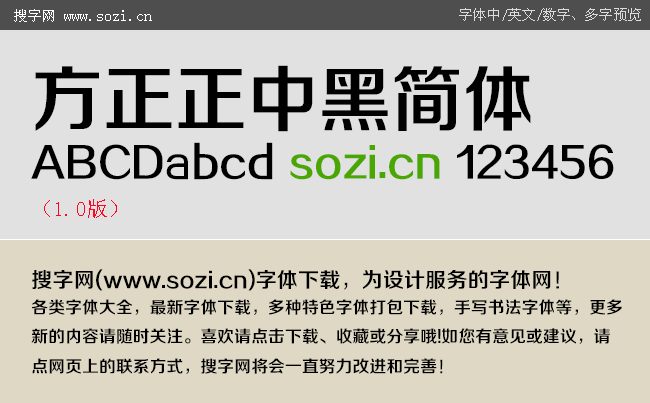
方正正中黑簡(jiǎn)體
搜字網(wǎng)提供一方正正中黑簡(jiǎn)體中文藝術(shù)字體下載,正黑體取傳統(tǒng)黑體結(jié)構(gòu),筆形全部采用平行、垂直與弧度的流線(xiàn)形設(shè)計(jì),簡(jiǎn)潔易識(shí)、美觀大方,具有個(gè)性,加之鏡像對(duì)稱(chēng)的現(xiàn)代構(gòu)成形式,達(dá)到莊重與簡(jiǎn)潔有機(jī)融合、設(shè)計(jì)感與閱讀功能兼?zhèn)涞淖罱K效果。適合書(shū)籍排版,報(bào)紙排版,海報(bào)設(shè)計(jì),包裝設(shè)計(jì)等廣告設(shè)計(jì)場(chǎng)合應(yīng)用。